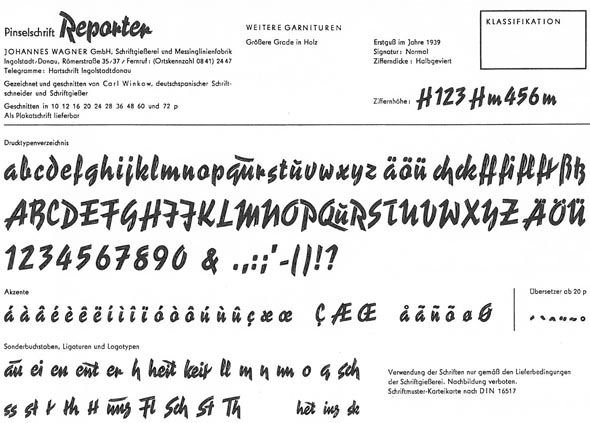
Warum gibt es keine qu-Ligatur?
Warum gibt es eigentlich (so gut wie) keine qu-Ligatur?
Bei Großbuchstaben trifft man ja zumindest manchmal noch auf so eine Ligatur, aber bei den Kleinbuchstaben scheint sie sich nicht durchgesetzt zu haben.
Weiß jemand, woran das liegt?
Ligaturen haben ihren Ursprung in der Bleisatz- / Buchdruck-Zeit. Und da wurden nicht häufige Buchstabenverbindungen auf einen Kegel gegossen (sonst hätten wir ja keine ff- und fi-Ligaturen sondern vor allem Verbünde wie en), sondern Buchstaben, die sich sonst physisch behindert hätten. Der obere Bogen vom f wurde in der Regel überhängend gegossen, das heißt, der Kegel war schmaler als der Buchstabe. Wenn jetzt ein Buchstabe mit Oberlänge folgte, konnte der überhängende f-Bogen abbrechen. Dies konnte man zwar verhindern, indem man diesen folgenden Buchstaben mit Blindmaterial absperrte, also auf Abstand hielt, dies war aber ästhetisch unbefriedigend. Es gab also eine Notwendigkeit für fi- und ff-Ligaturen, während man z. B. ein fb nicht brauchte, weil diese Buchstaben kaum aufeinandertreffen. Für ein qu wiederum gab es nie eine Notwendigkeit, weil diese Buchstaben sich gar nicht behindern und völlig konfliktfrei nebeneinanderstehen. Für Ligaturen aus rein ästhetischen Gründen gab es im Bleisatz keinen Raum — im buchstäblichen Sinne. Man hätte gar nicht gewußt, wo man die im Setzkasten noch hätte unterbringen sollen.
Es gab zwar einmal den Versuch, den Bleisatz zu revolutionieren, indem man alle denkbaren Ligaturen goß, auch mit mehr als zwei oder drei Buchstaben, um die Anzahl der Griffe des Setzers zu verringern und damit die Arbeit zu beschleunigen. Das war aber wegen der Fülle der Verbünde nicht praktikabel und hat sich nie durchgesetzt.
Verstehe ich, aber warum gibt es dann ch- und ck-Ligaturen? Da stören sich die Buchstaben doch auch nicht, oder?
Pachulkes Beitrag ist zwar richtig, aber behandelt auch nur einen von vielen Punkten von Ligaturen. Die Aussage »Ligaturen kommen aus dem Bleisatz« führt schnell auf eine falsche Fährte. Ein W ist auch eine Ligatur, die nun ja bekanntlich nicht aus dem Bleisatz kommt.
Zu der Ursprungsfrage: Warum meinst du denn, dass es eine qu-Ligatur geben sollte? Ich verstehe die Frage schon nicht. Weil sie als ein Laut verwendet werden können? Es gibt unzählige Laute im Deutschen, die durch zwei Buchstaben abgebildet werden und natürlich nicht legiert werden. Warum auch?
Der Einsatz von Ligaturen hatte ursprünglich eher einen optischen Sinn zu erfüllen. Gutenbergs Qualitätsanspruch war es, den handgeschriebenen Büchern so nahe als möglich zu kommen. Zu diesem Zweck fertigte er für seine 42-zeilige Bibel neben vielen Buchstabenvarianten insgesamt 83 Ligaturen an. Er erreichte damit annähernd den Eindruck des Handgeschriebenen.
Der Bedarf an Ligaturen verringerte sich mit der Rationalisierung bzw. Industrialisierung des Buchdrucks und beschränkte sich auf die notwendigen Ligaturen, wie oben Pachulke beschrieb.
Bei vielen der heute verwendeten Schriften, die nicht auf alte Vorbilder zurückgreifen, kommt man ohne Ligaturen wie ch und ck etc. aus.
Spontan, als ich den Eröffnungspost las, dachte ich, dass es bei Qu/qu gar keinen Anlass für eine Ligatur gibt, weil sich die beiden Buchstaben formal doch gar nicht in die Quere kommen. Somit ist auch keine außerordentliche Unterschneidung notwendig, die eine Ligatur im Bleisatz notwendig gemacht hätten (außer bei sehr ungewöhnlichen Q-Formen vielleicht). Und mir fällt auch auf die Schnelle kein Beispiel ein, bei dem eine Ligatur unbedingt benötigt würde, um den Schriftanwender von einer unsachgemäßen Worttrennung zwischen q und u abzuhalten. :-)
Verstehe ich, aber warum gibt es dann ch- und ck-Ligaturen? Da stören sich die Buchstaben doch auch nicht, oder?
Die kommen aus der Fraktur und haben nicht technische, sondern historische Gründe, über deren Sinn und Unsinn hier im Forum schon viel virtuelle Tinte vergossen wurde.
Zu der Ursprungsfrage: Warum meinst du denn, dass es eine qu-Ligatur geben sollte? Ich verstehe die Frage schon nicht. Weil sie als ein Laut verwendet werden können? Es gibt unzählige Laute im Deutschen, die durch zwei Buchstaben abgebildet werden und natürlich nicht legiert werden. Warum auch?
Der Gedanke, Laute zu Ligaturen zusammenzufassen, hat durchaus seinen Charme, auch wenn dies im technischen Sinne unnötig ist. Ich könnte mir sogar vorstellen, daß Ligaturen wie ei, ss, sch, ung und en (oder eben auch qu), wenn sie etabliert wären, sogar einen Beitrag zur Lesefreundlichkeit leisten würden — was nun leider nicht überprüfbar ist, da man sie nicht testweise etablieren kann.
Die aktuelle Schrifttechnologie würde solch eine Ligaturenschwemme sogar erstmalig mit vertretbarem Aufwand ermöglichen.
Ich bin nicht der Meinung, dass es eine qu-Ligatur geben sollte, ich bin nur neugierig. Über Ligaturen habe ich viel gelernt - vielen Dank! - und weiß jetzt, dass ich das gar nicht meinte. ;-) Ich wollte eigentlich wissen, warum das qu historisch nicht zu einem Buchstaben verschmolzen ist, oder in den Worten meines kleinen Neffens, der gerade in der Schule das Q gelernt hat und mich überhaupt darauf gebracht hat:
"Wenn auf ein q immer ein u folgt, warum lässt man das u dann nicht einfach überall weg?"
Nicht immer folgt ein u dem Q:
… Qigong, Qindar, qkm … (Quelle: Duden)
Nicht immer folgt ein u dem Q:
… Qigong, Qindar, qkm … (Quelle: Duden)
Das sind immer so die Sachen, die man beim Scrabble verzweifelt sucht, wenn man noch ein Q hat und alle u schon auf dem Brett liegen.